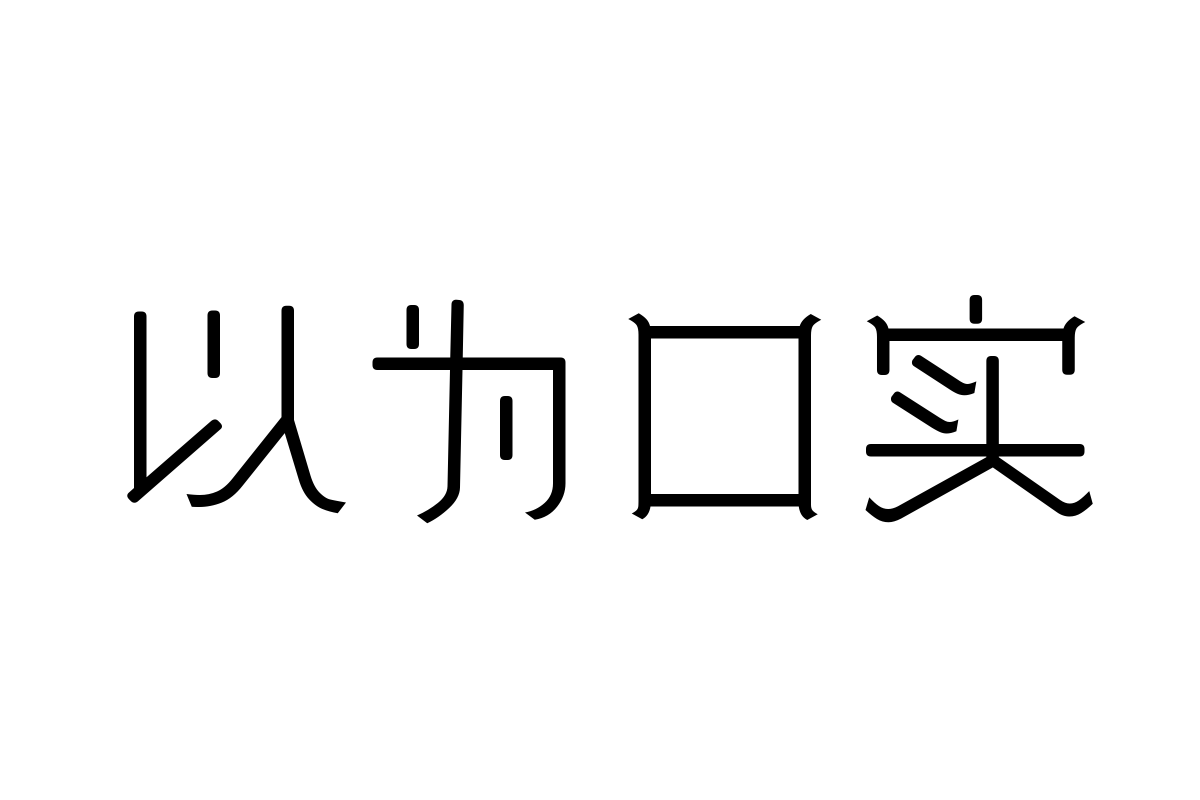
三极奕修简体字体是一款由日本公司开发的无衬线字体,具有现代感和简洁的线条。它的设计灵感来源于日本的传统文化,如茶道、花艺等,因此在字形上呈现出一种优雅而精致的风格。
三极奕修简体字体的特点是:
1. 无衬线:这种字体的特点是没有衬线,线条更加流畅,给人一种现代感。
2. 简洁:这种字体的笔画简单,结构清晰,易于阅读和书写。
3. 优雅:这种字体的设计灵感来源于日本的传统艺术,因此具有一种独特的优雅气质。
4. 通用性强:这种字体适用于各种类型的文本,包括标题、正文、广告牌等。
总的来说,三极奕修简体字体是一款适合用于商业、文化、教育等领域的无衬线字体。